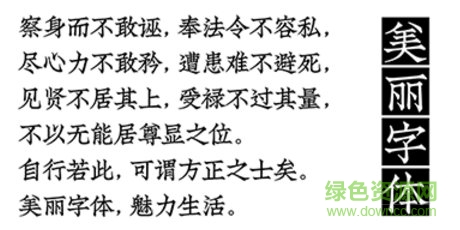
聚珍體是喜鵲造字推出的一款商用字體,風格上與仿宋體冀教接近,筆畫端正秀氣靜美,有著極佳的藝術美感,給人清爽亮麗的品味,綠色資源網今日推薦!
適用于排版古典清新風格的正文或標題文字需求,
如傳統(tǒng)文化、古籍排版、國風品牌、請柬等。
聚珍仿宋體在創(chuàng)制之初的排印對象便是古籍善本,適用于豎排的版式系統(tǒng),標題文字與正文文字無字號字形上的變化。雖然單個字形來說很有特點,具有宋版的仿歐體印刷字體優(yōu)秀的特點。但是后來人們的閱讀習慣發(fā)生了極大的轉變,漸漸習慣于橫排文字以及標題字與正文字體按標題級別區(qū)分的版式設計。這種轉變是隨著人們閱讀資料內容的轉變而來的,更多的廣告和插頁出現在書籍和期刊、報紙當中,新的形式和內容考驗了仿宋體的多樣性和可閱讀性。因此,當時幾乎沒有出現 “聚珍仿宋體”作為正文橫排的例子。這是與“聚珍仿宋體”的設計理念和字體特征決定的。